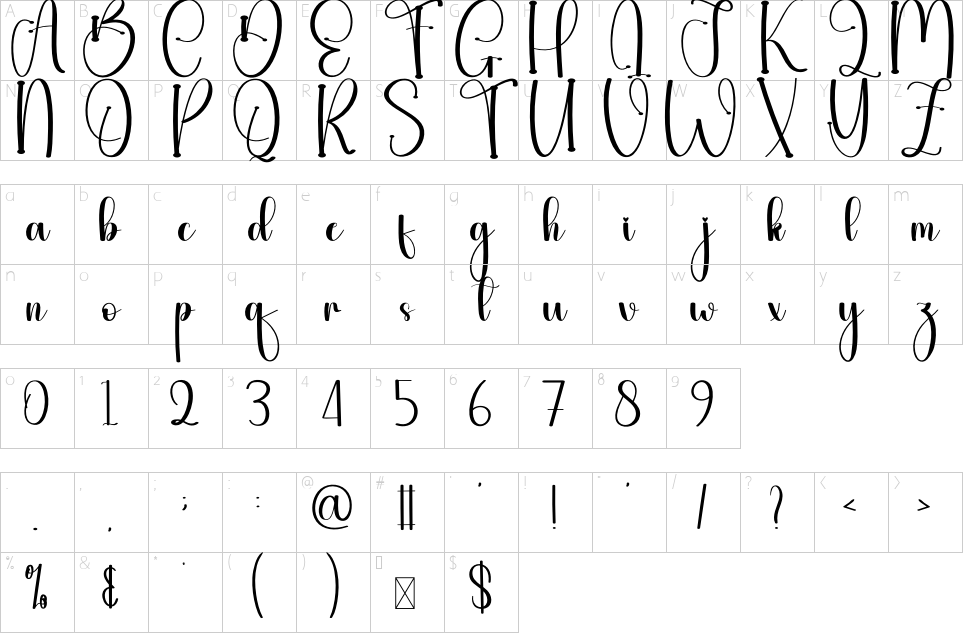
Descubra a Auntie Font, uma elegante e confortável fonte para uso em Windows e Mac. Desenvolvida por William Jhordy, essa fonte foi projetada para oferecer um estilo que combina modernidade e simplicidade, perfeitamente adaptada para uso em design gráfico e escrita cotidiana. Com um design cuidadosamente elaborado, a Auntie Font é ideal para manuseios precisos e suaves, tornando-a uma opção versátil para qualquer projeto. Não é à toa que ela já foi baixada 287 vezes. Se você está buscando uma fonte para seu próximo projeto, a Auntie Font pode ser uma escolha interessante. Descubra agora e adquira a sua versão gratuita.